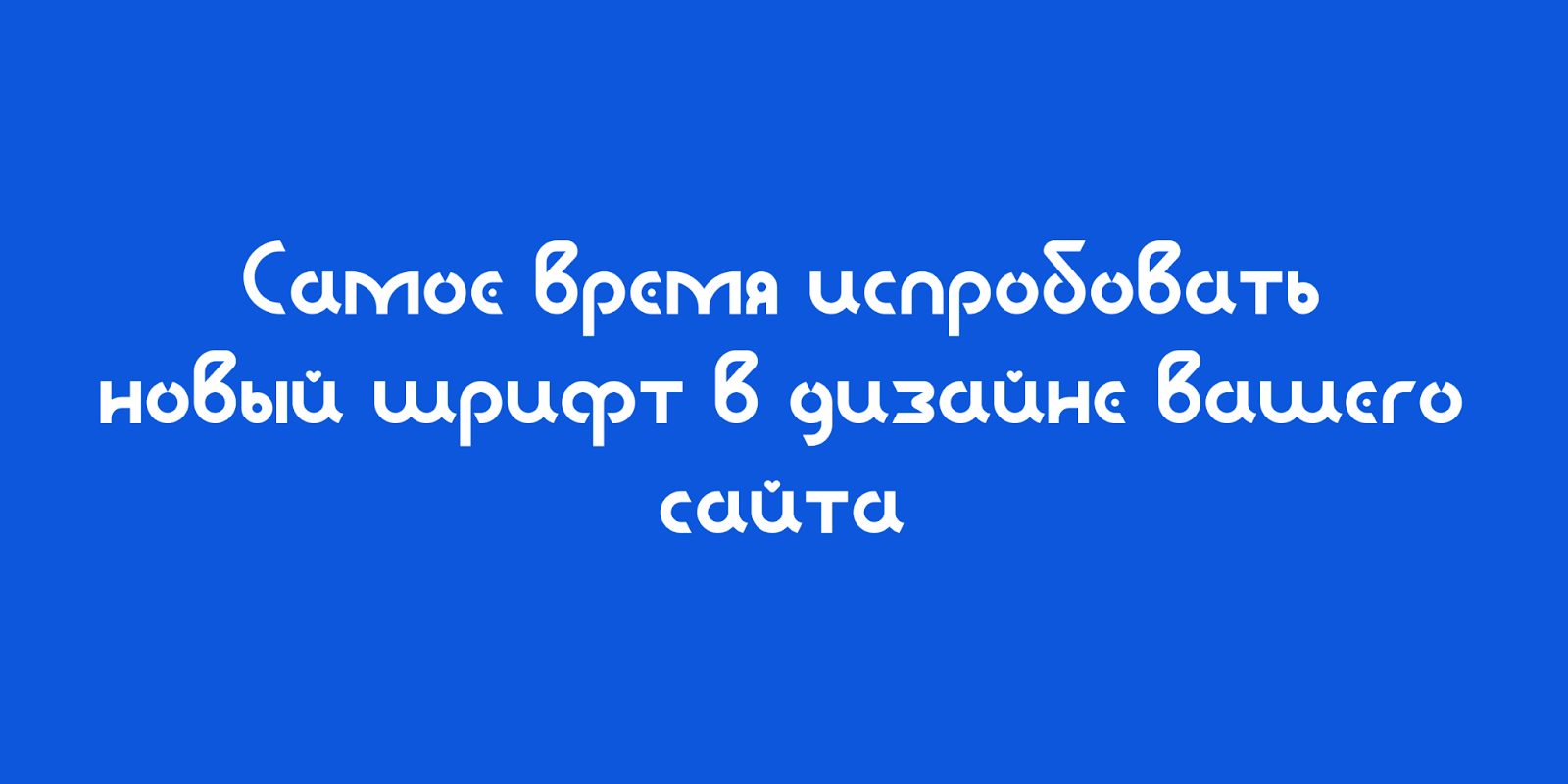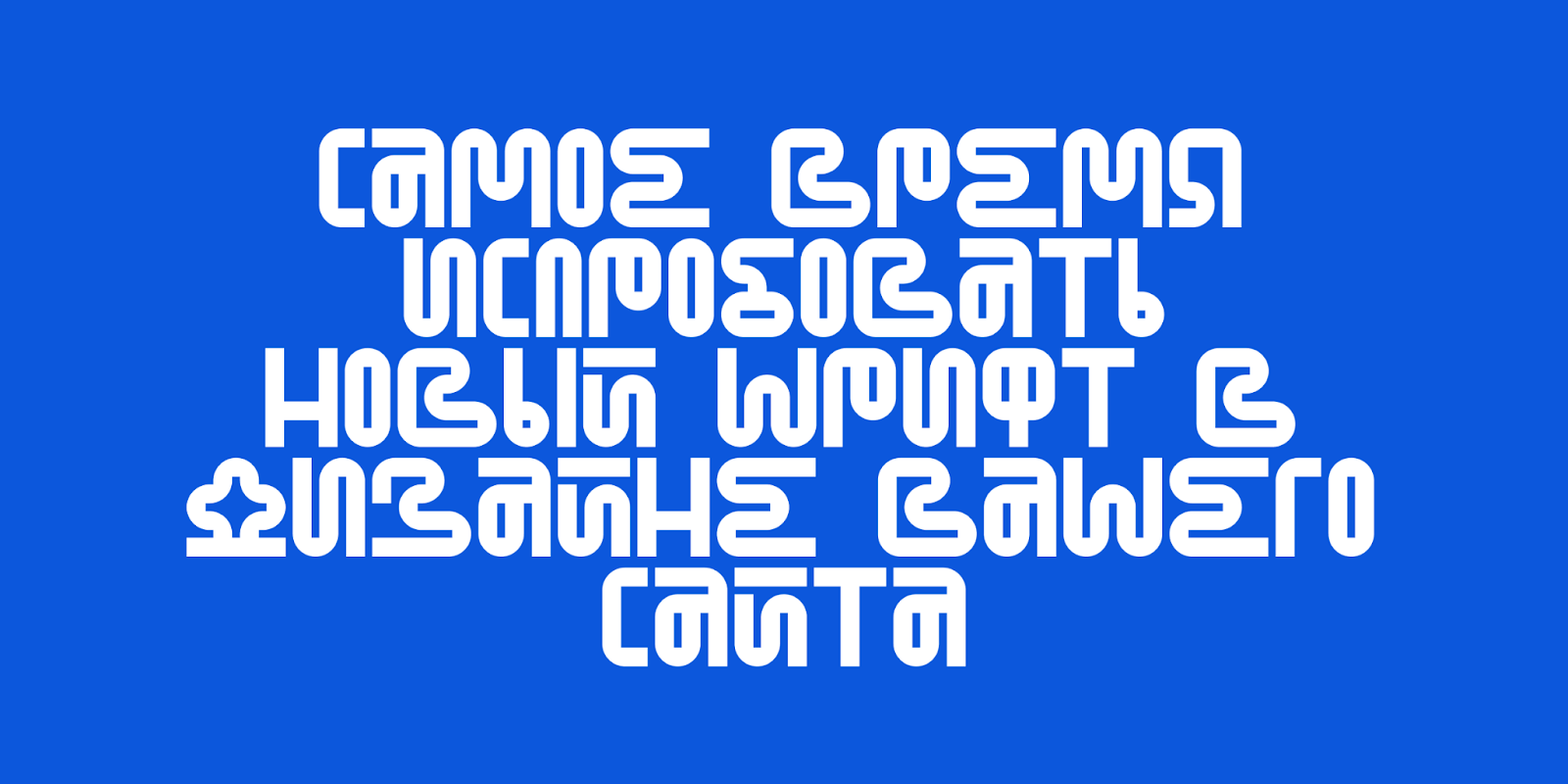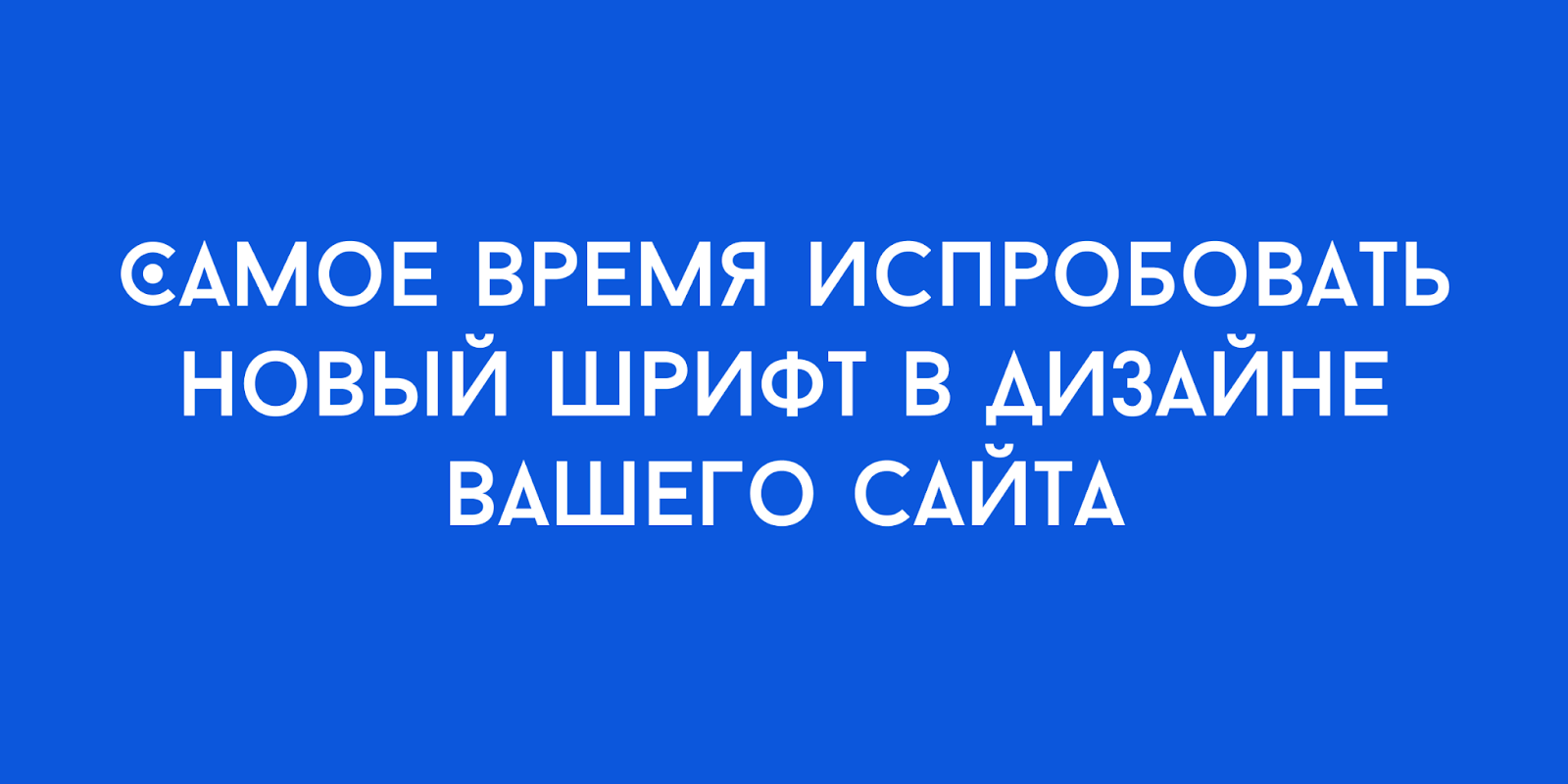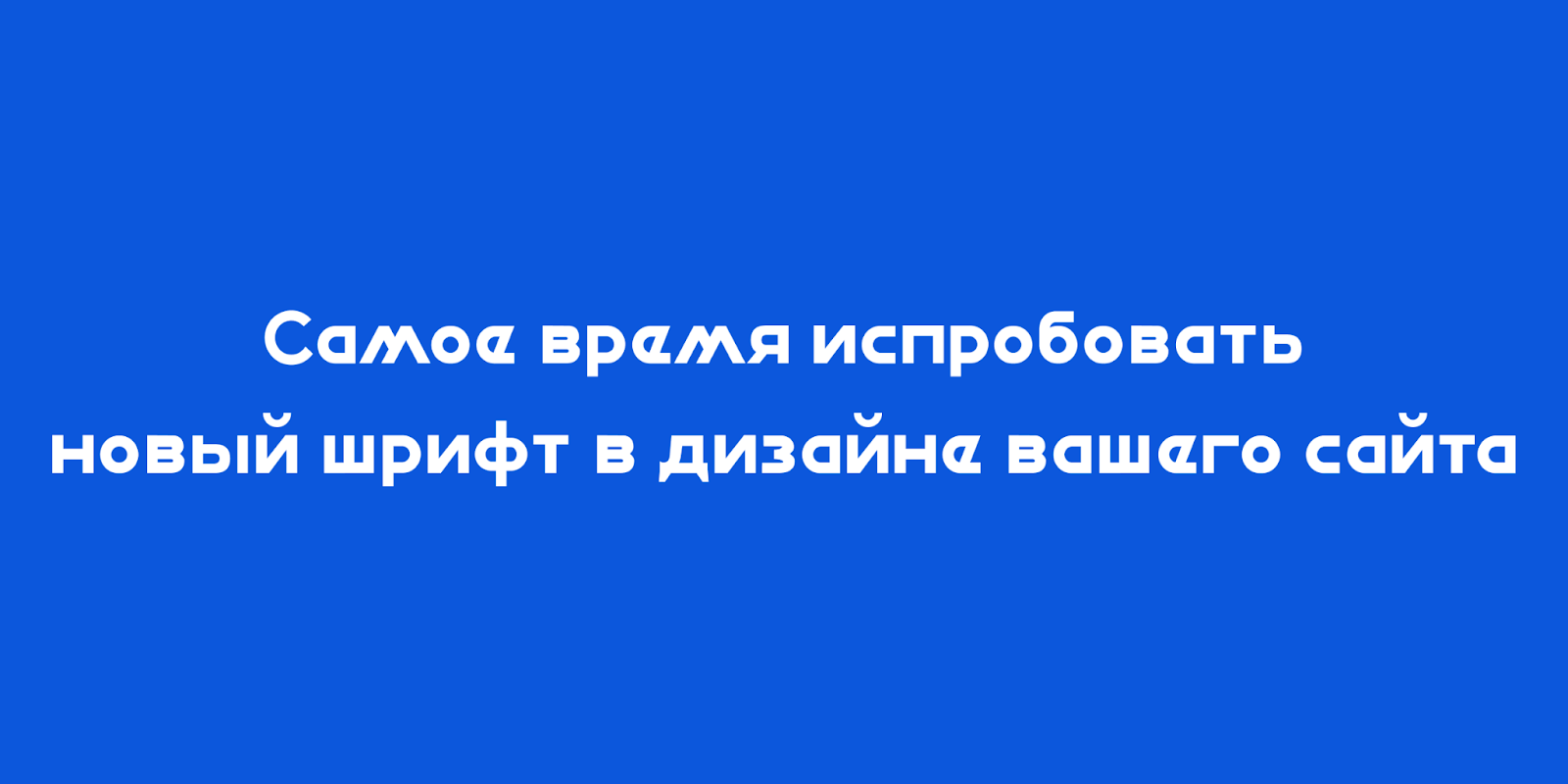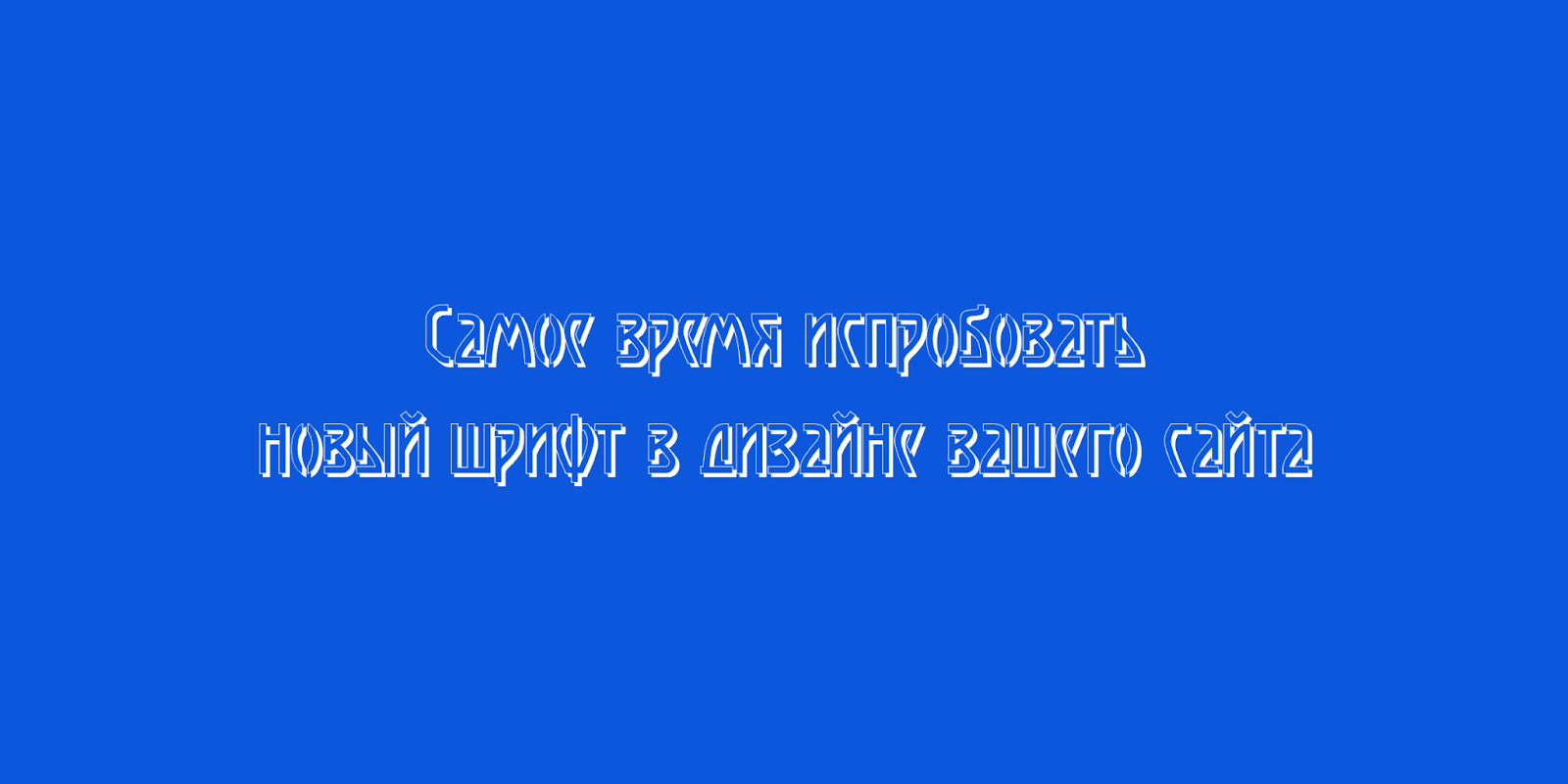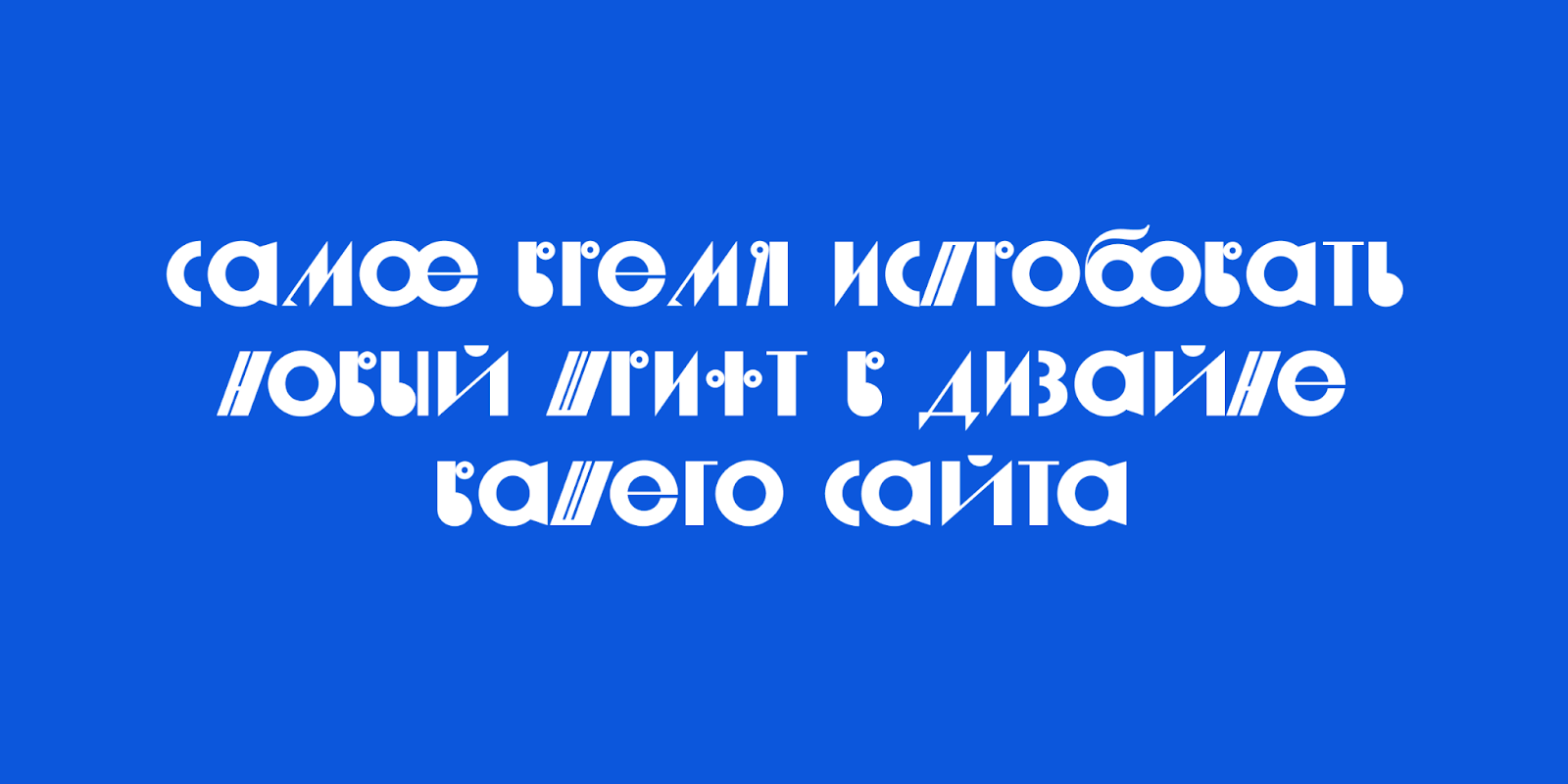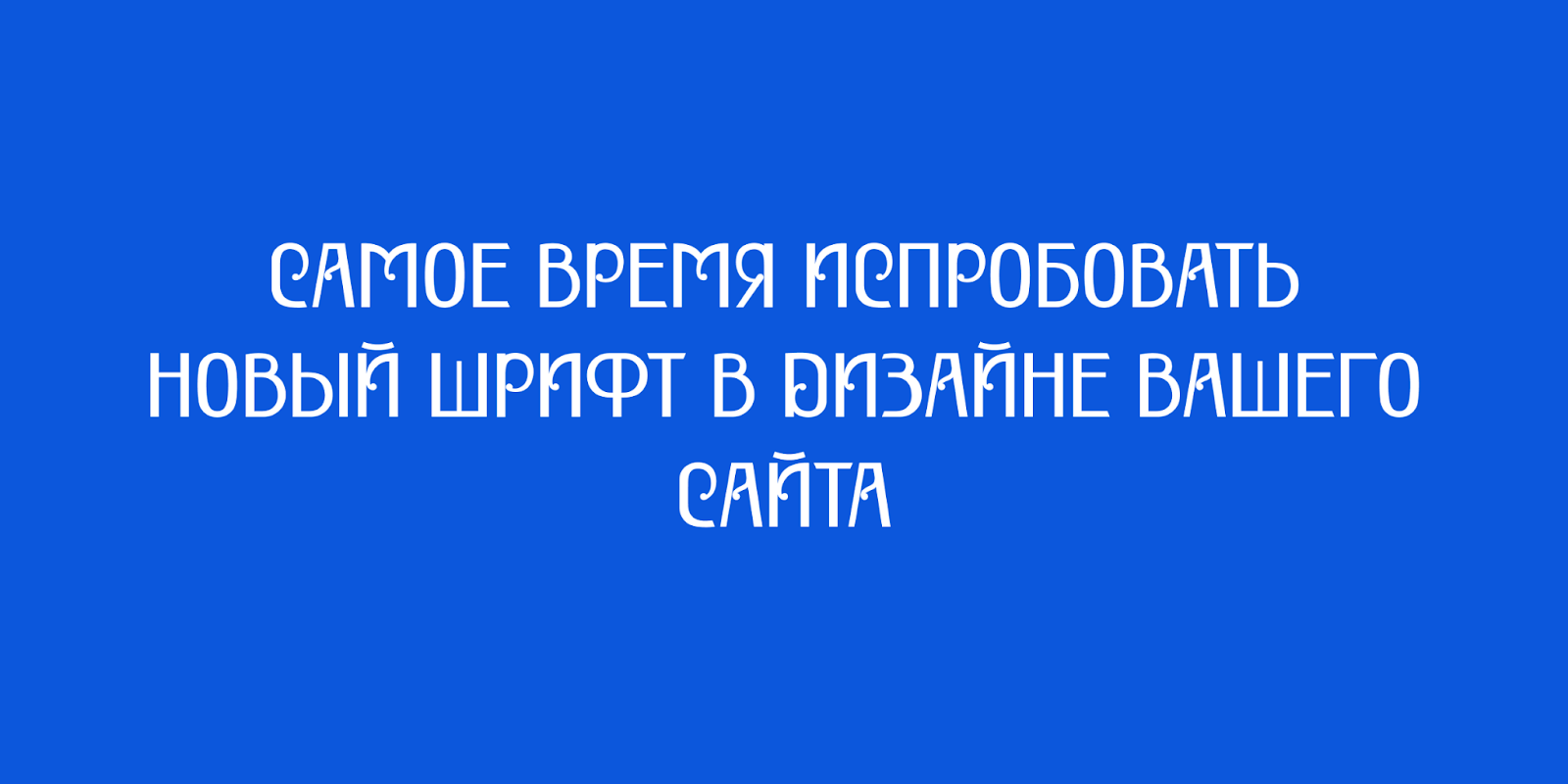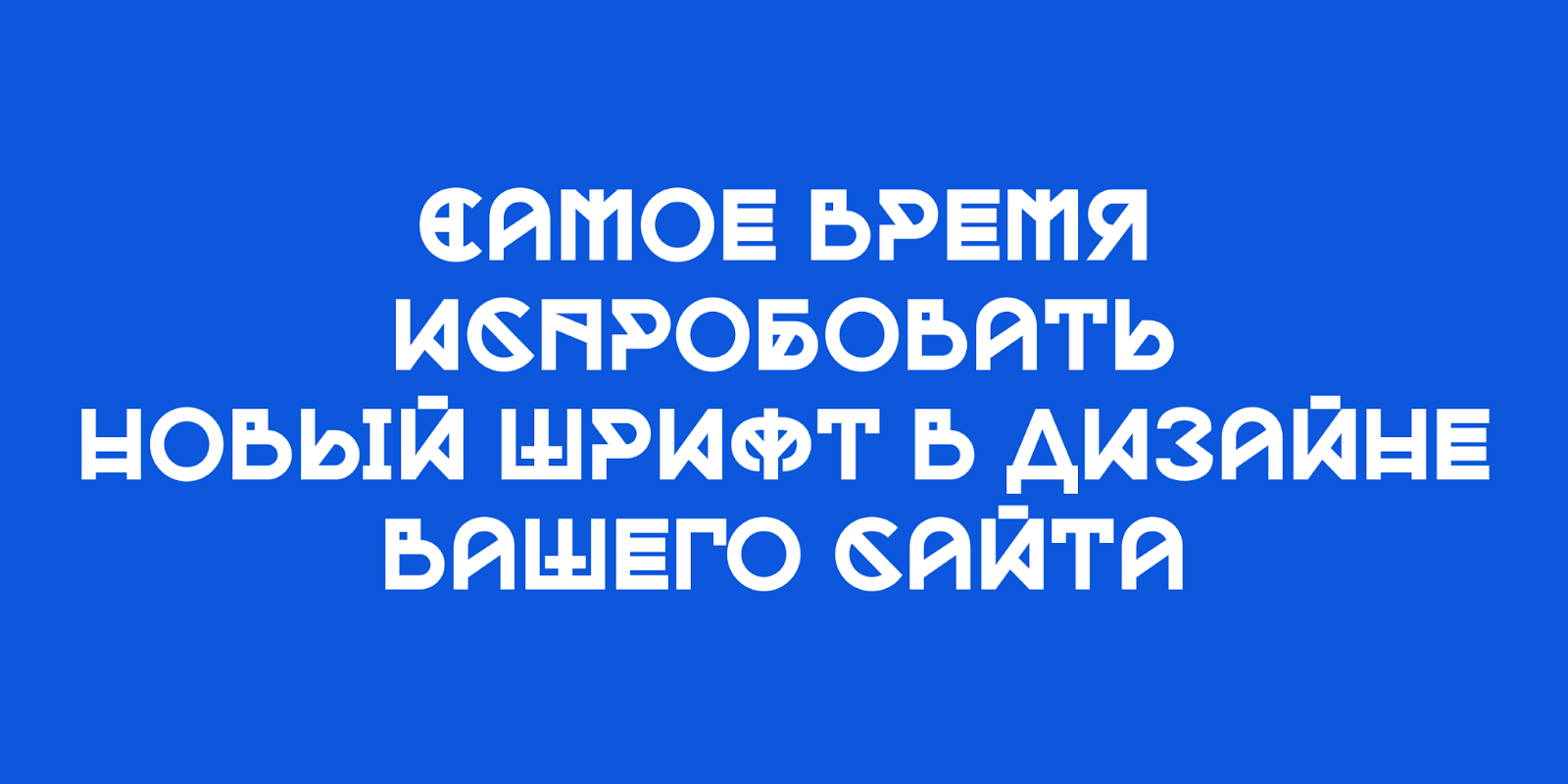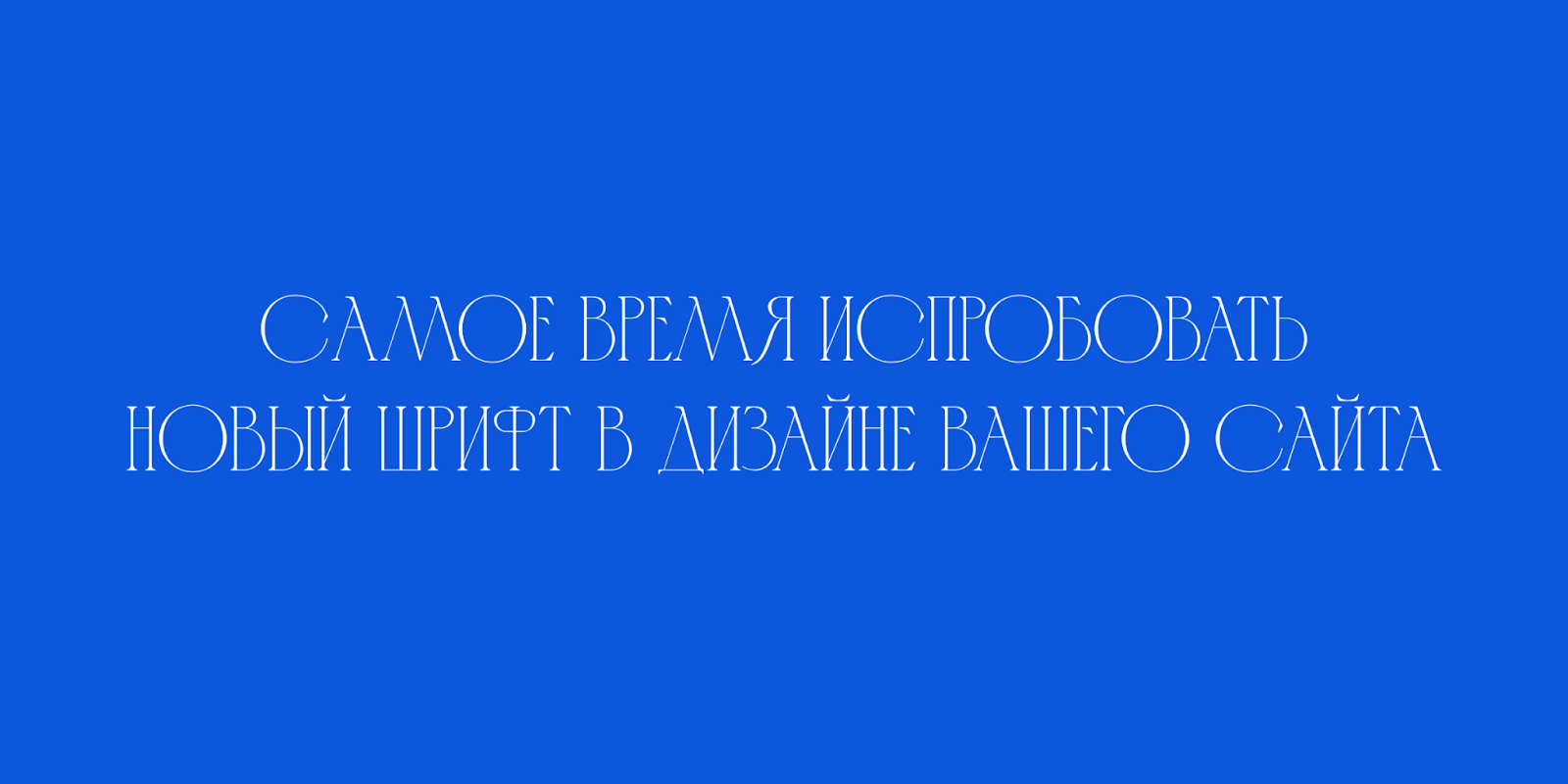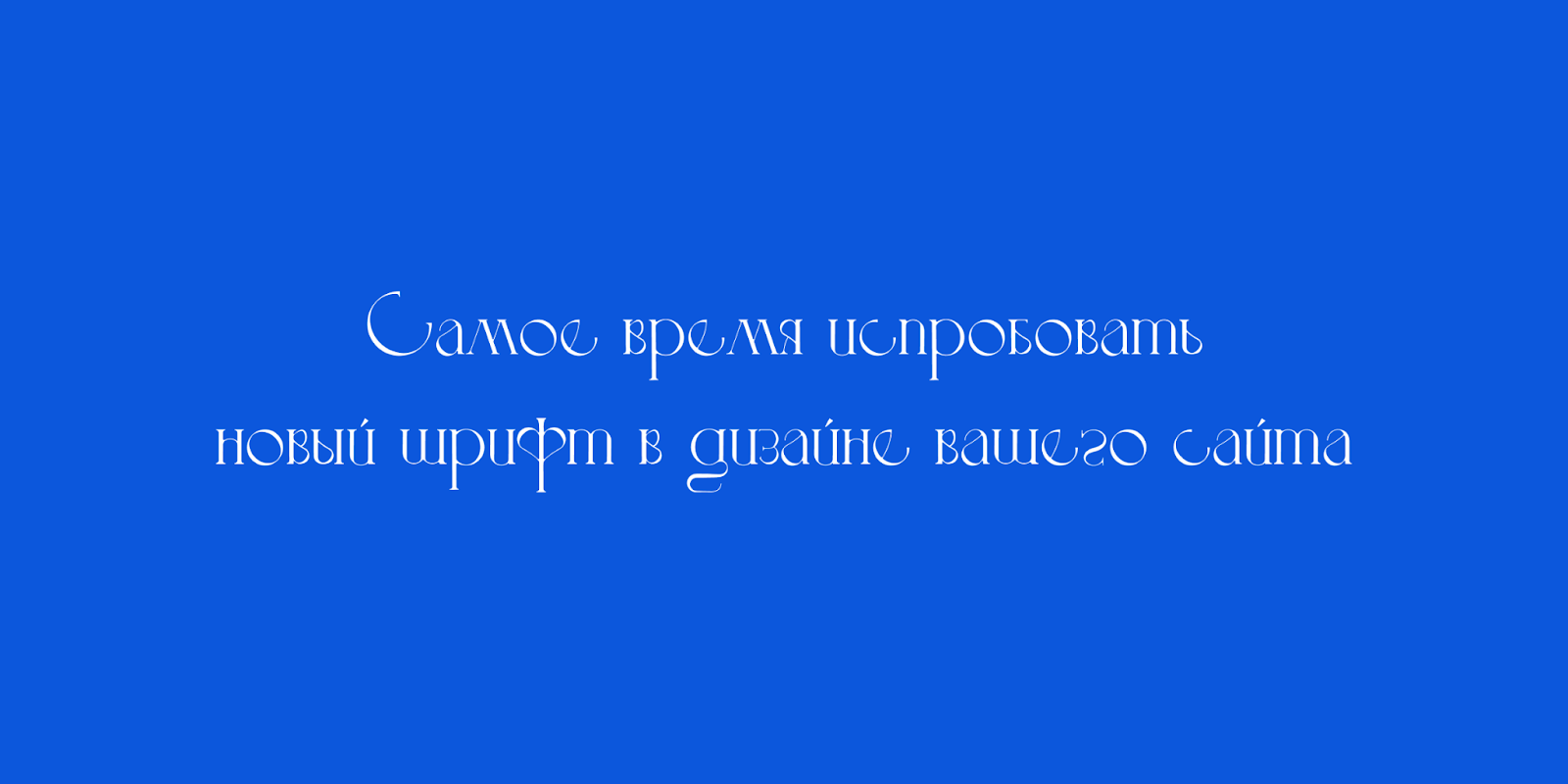
Типографика представляет собой нечто большее, чем простое средство передачи информации. Шрифты создают эмоциональную связь между контентом и читателем, определяют скорость обработки материала и влияют на обработку решений пользователями. В условиях растущей конкуренции за внимание правильный выбор шрифтов становится важным элементом любого проекта.
Фундаментальные принципы кириллической типографики
Источники уникальных шрифтов
Топ-15 выдающихся шрифтов 2025 года
Принципы эффективного применения шрифтовт
Заключение
Фундаментальные принципы кириллической типографики
Структурные особенности шрифтов
Шрифты имеют сложную структуру, состоящую из элементов и характеристик. Понимание анатомии шрифта необходимо для выбора и использования типографики в дизайне.
Основные линии и измерения
Структурные особенности шрифтов позволяют классифицировать их по различным признакам:
• По наличию засечек : с засечками (с засечками) и без засечек (без засечек)
• По контрасту : контрастные, малоконтрастные, неконтрастные.
• По насыщенности : светлые, нормальные, полужирные, жирные.
• По пропорциям : нормальные, узкие, широкие.
• По наклону : прямые, курсивные, наклонные.
Понимание структурных шрифтов помогает дизайнерам и типографам выбирать подходящие гарнитуры для определенных задач, повышать читаемость, эстетические качества и функциональность текста.
Источники уникальных шрифтов
Топ-15 выдающихся шрифтов 2025 года
1. Baron Neue
Baron Neue — современный геометрический шрифт без засечек от голландского дизайнера Франка Хеммекама. Дисплейный шрифт с жирными, чистыми линиями и строгой геометрией. Включает 6 начертаний, поддерживает 50+ языков. Идеален для логотипов, заголовков и брендинга. Бесплатен для личного использования.
2. Bolgarus Beta
Bolgarus Beta — экспериментальный футуристический шрифт, который сочетает в себе современную типографику с элементами культурного символизма. Это светодиодный шрифт с ярко выраженным концептуальным характером и нестандартным подходом к форме буквы.
3. Cakra
Cakra — экспериментальный светодиодный шрифт, обладающий неповторимой индивидуальностью и современным характером. Это универсальный шрифт, созданный для художественных проектов и креативных решений, требующих выразительной типографики.
4. GRUNT_v1
GRUNT_v1 — экспериментальный светодиодный шрифт, созданный дизайнером Евгением Артсебасовым. Это дерзкий, неотшлифованный шрифт с ярко выраженной индивидуальностью, предназначенный для создания мощных визуальных заявлений.
5. Kontanter
Kontanter — экспериментальный моноширинный светодиодный шрифт, созданный как творческая интерпретация классического геометрического гротеска. Шрифт сочетает в себе строгость моноширинной типографики с солнечностью современного дизайна.
6. NowGrotesk
NowGrotesk — ретро-футуристический универсальный шрифт с геометрическими чертами и вдохновением в стиле арт-деко. Это экспериментальный дисплейный шрифт, созданный для создания ярких заголовков и веселых логотипов.